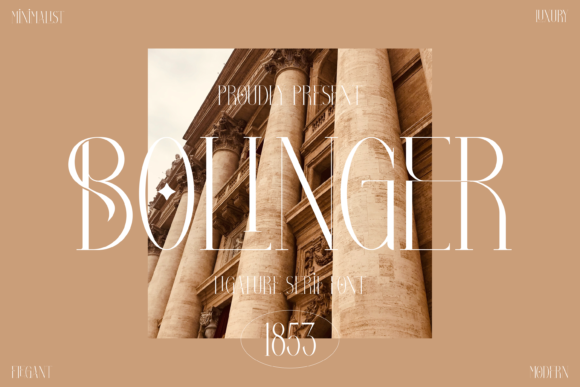
[Creativefabrica] Bolinger Font (2021)
Bolinger - это изысканный и шикарный шрифт с засечками, который впечатляет своими уникальными символами.
Это прекрасный вариант для слов, которые должны выделяться на общем фоне!